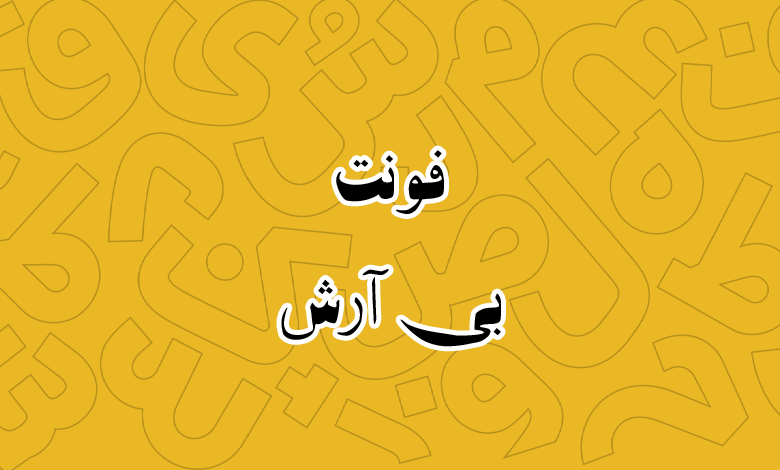
فونت بی آرش (B Arash)
فونت بی آرش یا فونت آرش (به انگلیسی: B Arash) از سری فونت‌های رایگان طراحی شده توسط برنا رایانه در دهه هفتاد است. این فونت رایگان TTF دارای ظاهری فانتزی است که در تمامی حروف خطوط افقی دارای ساختاری کشیده و ضخیم هستند؛ اما در مقابل خطوط افقی ظاهری بسیار نازک دارند.
چنین ساختاری فونت آرش را به یک فونت فانتزی تبدیل کرده که می‌توان از آن در عناوین، متون کوتاه و به طور کلی هر جا که نیاز به فونتی نمایشی داشته باشید استفاده کرد. در ادامه با دانلود فونت بی آرش با شما همراه هستیم و ویژگی‌های آن را بررسی می‌کنیم.
همانطور که در تصویر بالا می‌بینید، بی آرش یک فونت فانتزی و مناسب متون کوتاه است. این فونت برای متون بلند همچون کتاب یا تولید محتوا مناسب نیست؛ زیرا خوانایی لازم را ندارد و بیشتر برای زمانی که در ابعاد بزرگ تایپ شده باشد، زیبایی خود را نشان می‌دهد.
فونت آرش از زبان فارسی پشتیبانی می‌کند که می‌توانید برای زبان عربی نیز از آن استفاده کنید. اما کاستی موجود که در بیشتر فونت‌های سری بی وجود دارد، عدم پشتیبانی از اعداد فارسی «۰۴۵۶» است که در این قلم این اعداد به صورت نسخه عربی هستند.
همچنین زبان انگلیسی در این فونت فاقد گلیف اختصاصی بوده و از فونت جایگزین سیستم‌عامل استفاده خواهد شد. اما مجموعا این فونت برای زبان فارسی مناسب‌تر است.
با توجه به ساختار فانتزی و آزاد این فونت، کاربردهای آن بیشتر برای متون کوتاهی است که جنبه نمایشی دارند و با توجه به ضخامت متفاوتی که حروف در این قلم دارند، بهتر است در جایی استفاده شود که با سایز بزرگ تایپ شده باشند. از جمله کاربردهای این قلم می‌توان به موارد زیر اشاره کرد:
• عکس نوشته برای پست و ویدئو در شبکه‌های اجتماعی.
• استفاده در عناوین کتاب و مجلاتی که دارای محوریت داستانی، ادبی یا نمایشی هستند.
• استفاده در مطبوعات همچون چاپ انواع بیلبوردهای تبلیغاتی یا شعاری با ابعاد بزرگ.
• استفاده در سایت برای بخش‌هایی مثل اسلایدر که متون با ابعاد بزرگ تایپ شده و جلب توجه کنند.